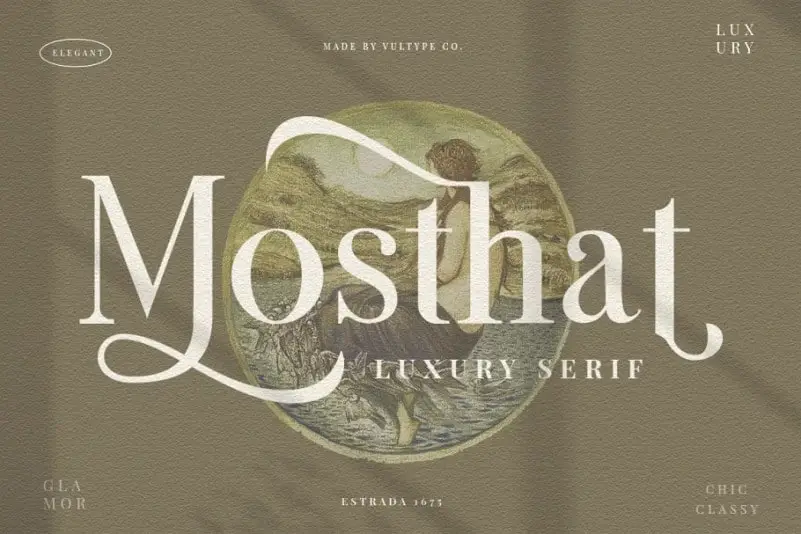
Mosthat Serif Font – Download Grátis
A “Mosthat Serif Font” é uma elegante solução para estilos serifados que captura a essência da moda com sua graça e simplicidade. Com um contraste minimalista que se tornou sinônimo de moda por décadas, esta fonte transmite modernidade e nostalgia em cada caractere. A sua aparência fresca e divertida combina perfeitamente com uma tipografia sans-serif ou script leve para criar um equilíbrio visual harmonioso. Suas linhas finas têm o poder de transformar o mais simples em algo singular, adequada tanto para a criação de logotipos quanto masthead’s e pull quotes. Como uma fonte que paira bem com outras tipografias minimalistas ou leves, a “Mosthat Serif Font” se destaca como um recurso gráfico versátil e atraente.